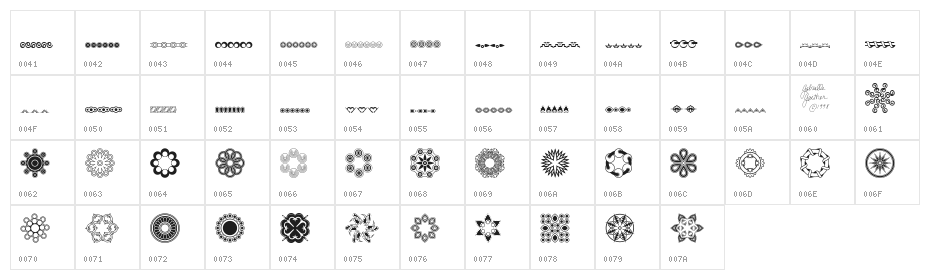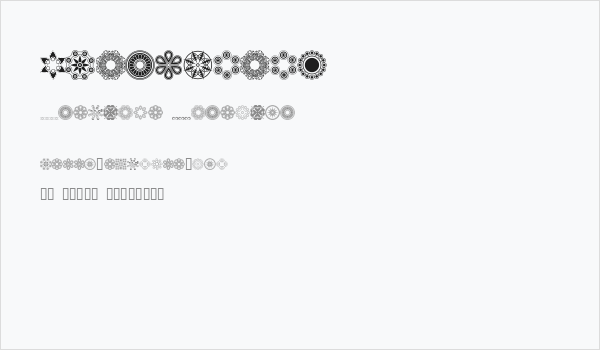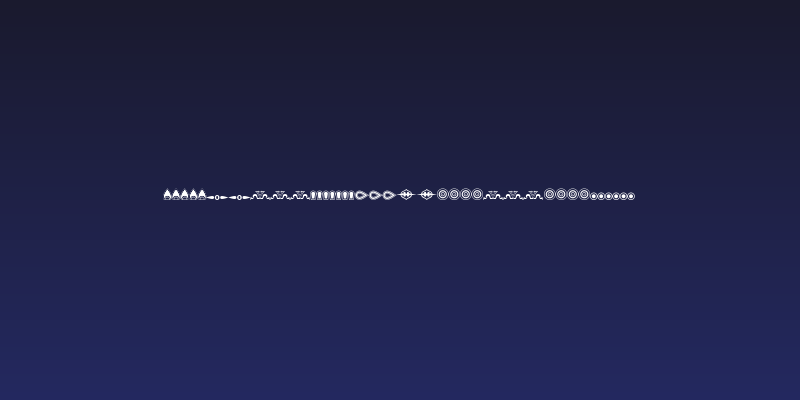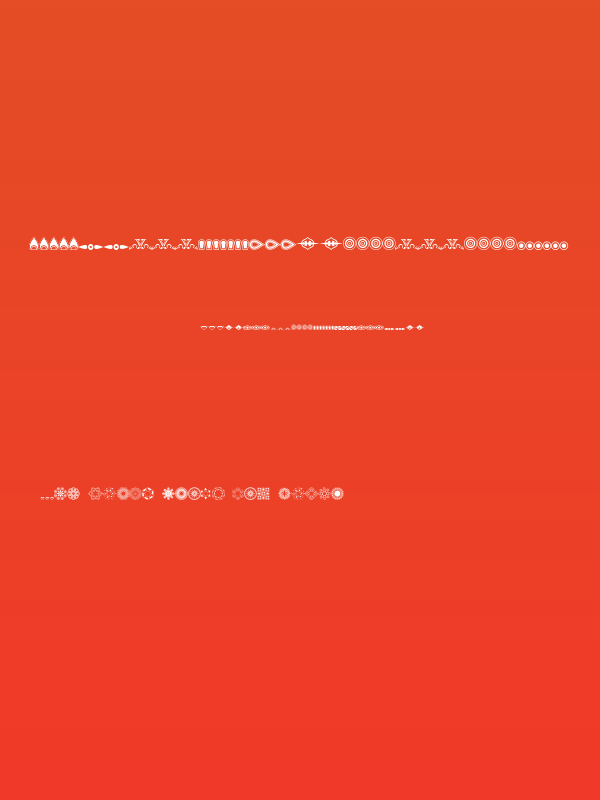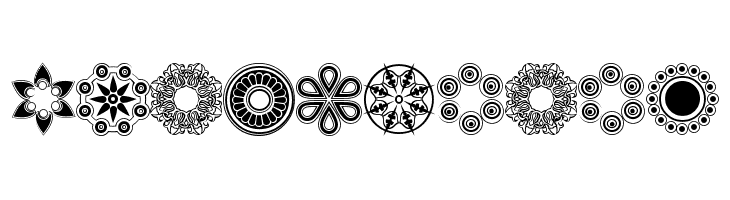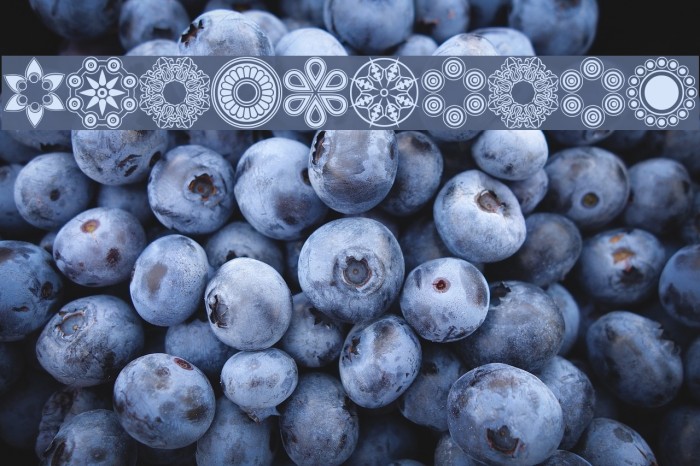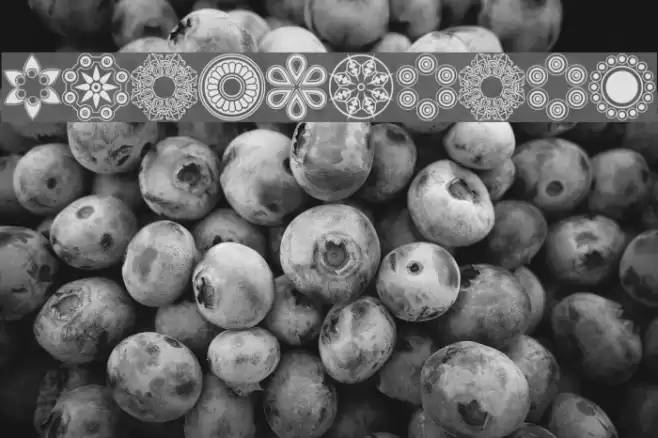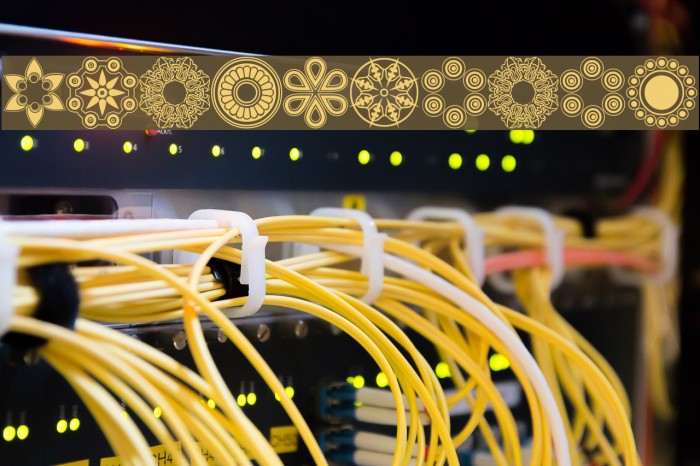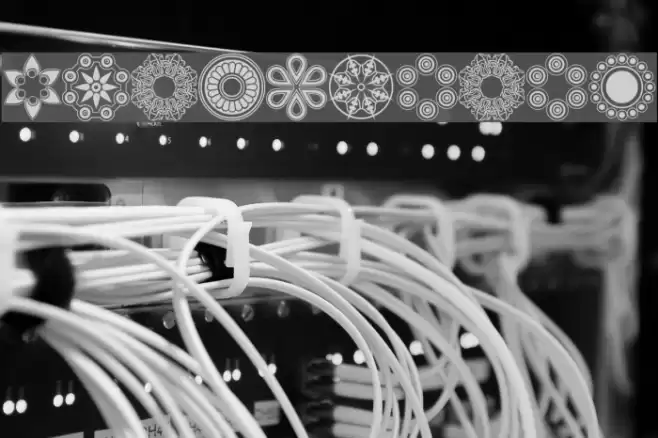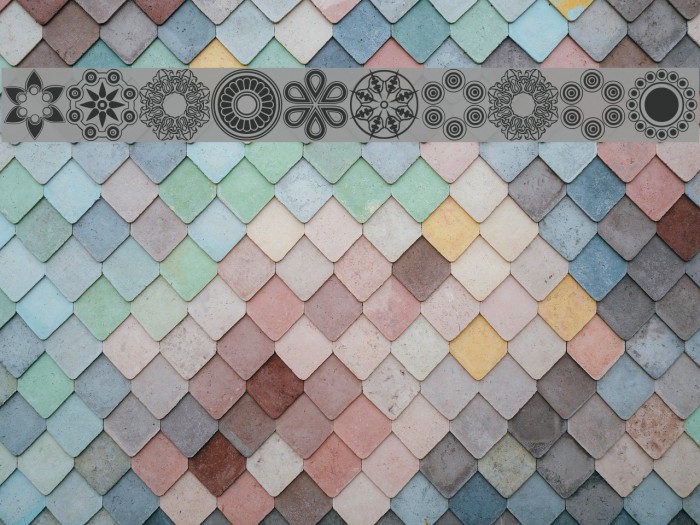
whirlygigs Font
| 全体的なスタイル | Decorative, Whimsical, Ornamental |
| 用途 | Borders, Dividers, Decorative elements, Scrapbooking |
| おすすめプロジェクト | Ideal for borders, dividers, invitations, scrapbooking, decorative headings, and creative design projects. |